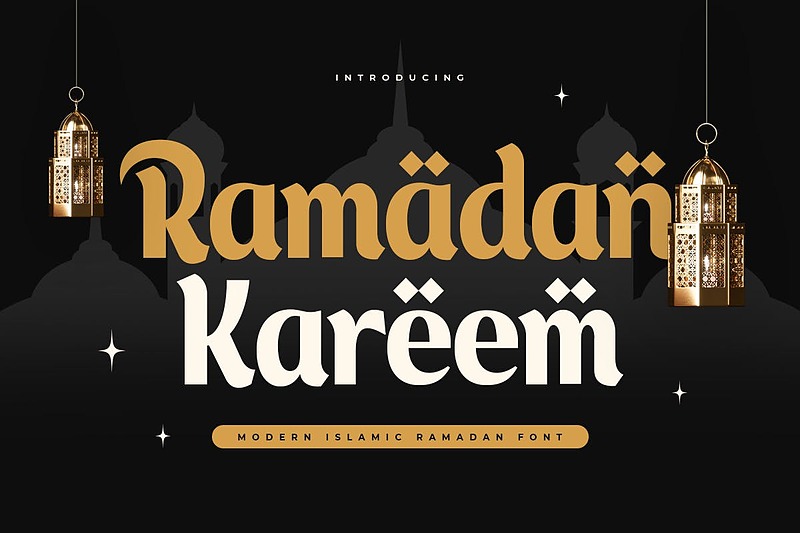
فونت انگلیسی اسلامیک رمضان کریم (Ramadan Kareem)
معرفی فونت رمضان کریم
رمضان کریم، یک فونت اسلامی مدرن است که دارای سبک مدرن، اسلامی و سیگنچرهای عربی می‌باشد و برای رویداد رمضان آماده شده است. می‌توانید با انتخاب گزینه‌های جایگزین آن‌ها به راحتی و تنها در چند ثانیه، به انوع مختلف و اشکال منحصربه‌فرد دست پیدا کنید. این یک فونت نمایشی با کنتراست متوسط است که برای پروژه‌های برندسازی رمضان، لوگو، طراحی‌های رمضانی، پست‌های رسانه‌های اجتماعی، تبلیغات، بسته‌بندی محصولات، طراحی محصولات، برچسب، عکاسی، واترمارک، دعوتنامه، لوازم‌التحریر و هر پروژه‌ای که نیاز به خوانایی بالا دارد، عالی است.
فونت رمضان کریم با موارد زیر آماده شده است:
• هر گزینه‌ای برای ایجاد تغییرات خلاقانه (ترکیبی از آلترنیت‌های خوش‌فرم)
• پیش‌نمایش الهام‌بخش از کارهایی که می‌توانید با این فونت انجام دهید
• دارای حروف کوچک و بزرگ
• اعداد و علائم نگارشی و کاراکترهای چندزبانه
• طبقه‌بندی: دکوراتیو